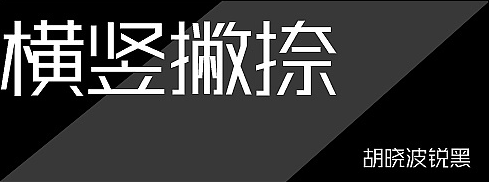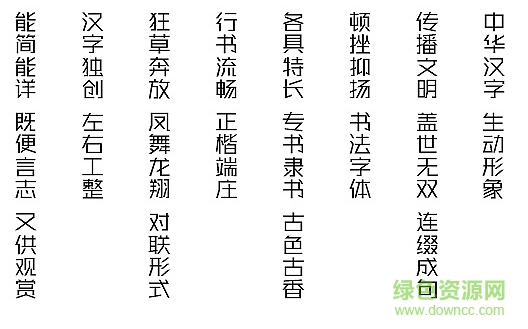
胡曉波銳黑是一款具有時(shí)尚元素、彰顯大氣靚麗的書法字體,廣泛適用于廣告設(shè)計(jì)、海報(bào)印刷、排版打印等行業(yè),喜歡的朋友趕緊來綠色資源網(wǎng)下載使用!
胡曉波銳黑是一款風(fēng)格時(shí)尚、筆畫簡單、動(dòng)感銳利的胡曉波字體,商業(yè)應(yīng)用廣泛,該字庫包含六千七百六十三個(gè)漢字字符。
胡曉波,他是一個(gè)造字夢想家,更是一個(gè)實(shí)踐家,從大二就開始致力于字庫與字形的設(shè)計(jì)開發(fā),通過幾年刻苦用心的學(xué)習(xí)、鉆研和摸索,在2011年底完成了第一套屬于自己的個(gè)人字庫——胡曉波美心體,第二年又完成了第二套“胡曉波趣圓體”。第三年上半年又完成第三套“胡曉波銳黑體”,下半年完成折紙?bào)w一級(jí)漢字3500個(gè)常用字符,同時(shí)組建團(tuán)隊(duì),合力開發(fā)更多字形豐富的字庫。
胡曉波的字體設(shè)計(jì),風(fēng)格多變,形象而生動(dòng),深刻體現(xiàn)出字體設(shè)計(jì)的藝術(shù)美感。其字體設(shè)計(jì)作品受到業(yè)內(nèi)的廣泛認(rèn)可并獲得良好贊譽(yù),在各大設(shè)計(jì)網(wǎng)都擁有相當(dāng)高的人氣,在設(shè)計(jì)圈內(nèi)也擁有較高的知名度。